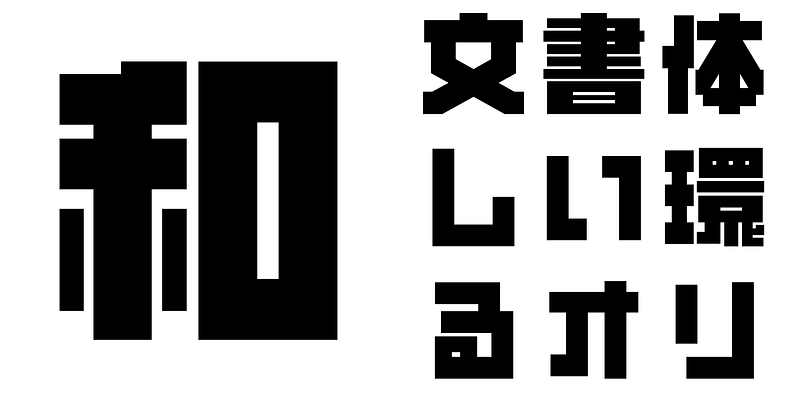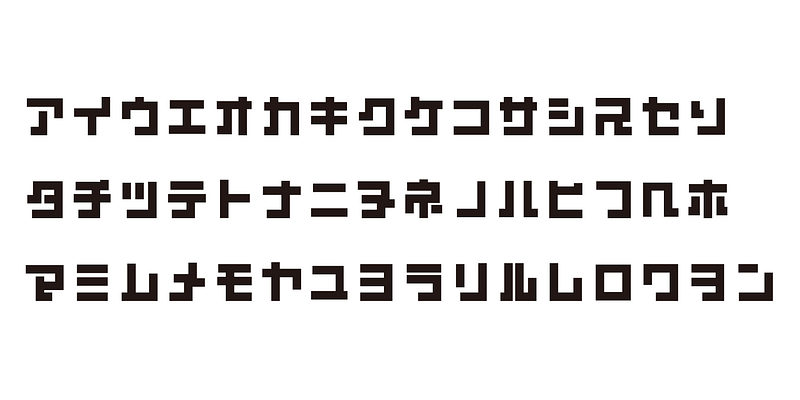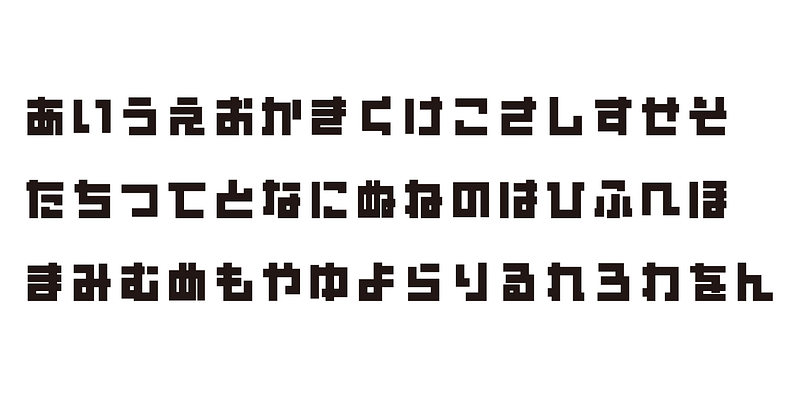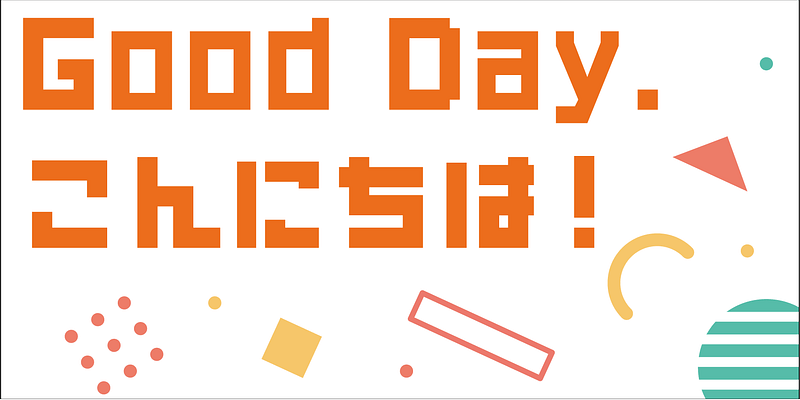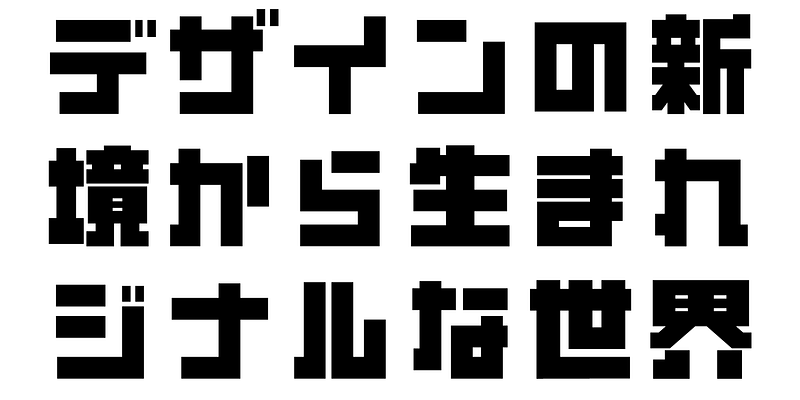
AB-DON a été imaginée pour donner une sensation de densité et de stabilité. Cette solidité est renforcée par l’utilisation de traits verticaux et horizontaux en tant qu’éléments principaux. Son design évoquant force et puissance, elle porte le nom de « DON », qui est une onomatopée japonaise pour décrire un son fort et grave.
Cette police comprend les 1 000 principaux caractères kanji choisis dans les tables de fréquence des caractères établis par les sociétés de presse, les maisons d’édition et les instituts de recherche linguistique, ainsi que 206 caractères kana et signes de ponctuation.
Dans la production de polices japonaises d’aujourd’hui, les 7 000 caractères de la norme JIS sont considérés comme essentiels. Mais toutes les polices ont-elles vraiment besoin de 7 000 caractères ? À l’ère de la phototypie, on utilisait beaucoup moins de caractères. FONT1000, un groupe de typographes indépendants, a commencé par se focaliser sur cette simple question. Nous avons sélectionné le minimum de 1 000 caractères kanji (idéographiques) nécessaires pour la composition en japonais et créé activement des polices pour les prendre en charge. Ce jeu de 1 000 caractères kanji a été créé en étudiant des données de fréquence des caractères compilées par des sociétés de presse, des maisons d’édition et des organismes de recherche linguistique, etc. Il comprend également des caractères syllabiques kana et des signes de ponctuation. FONT1000 a été créée en 2001 avec 25 designers et 25 polices de caractères. Aujourd’hui, nous avons 130 polices et comptons désormais près de 40 membres, ce qui permet de travailler sur des polices avec plus de caractères.